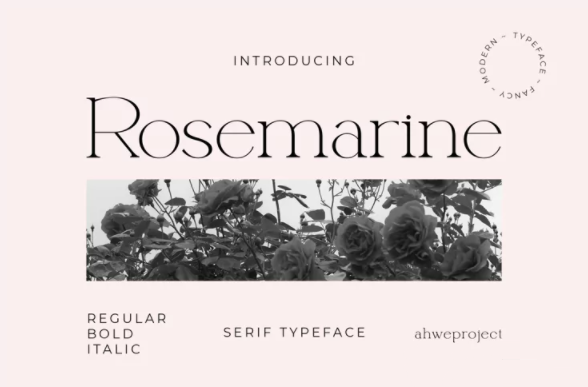
Название: Rosemarine Font (2021)
Rosemarine - элегантный и чистый шрифт с засечками.
Независимо от темы, этот шрифт станет прекрасным активом в вашей библиотеке шрифтов, поскольку он способен улучшить любое творение.